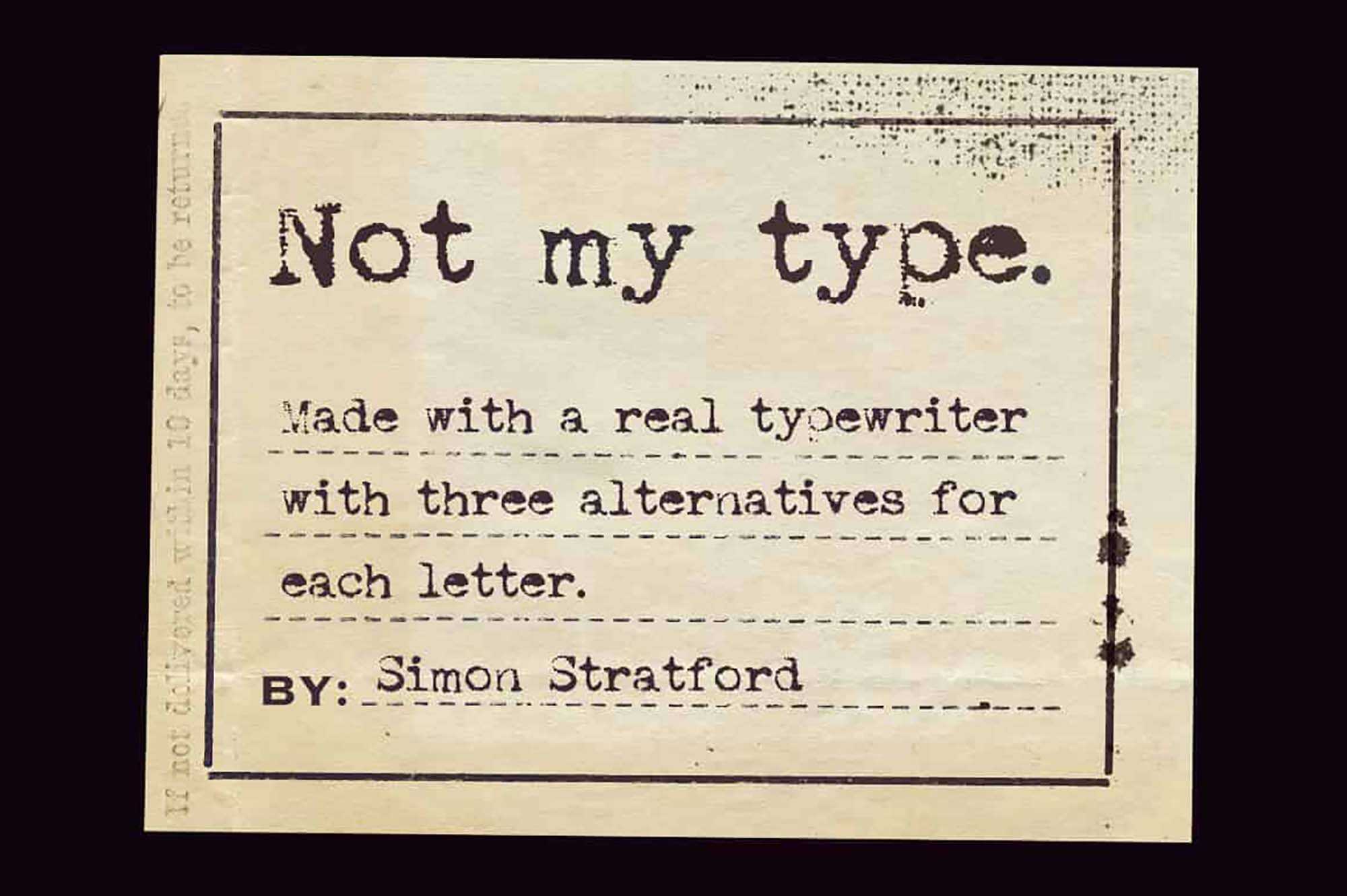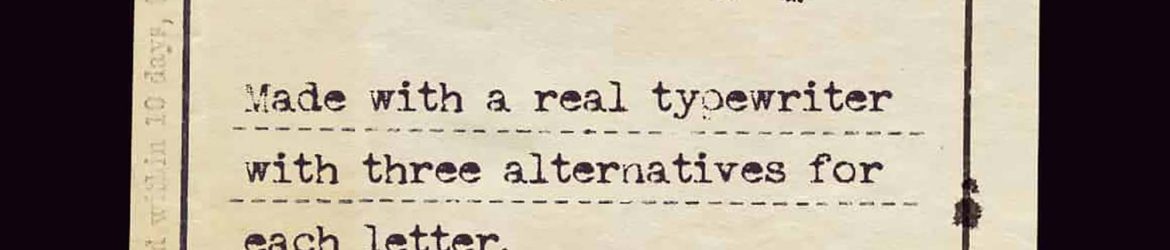
Nós estamos emocionados em apresentar Not My Type Font, uma nova fonte serif criada pelo designer Simon Stratford usando um teclado de escrita real. Essa fonte traz uma experiência única e autêntica, com a versão original e alternativas para cada letra, permitindo-lhe explorar infinitas combinações de texto e tornar seu design mais criativo. Este download inclui uma ampla gama de aplicações para diferentes projetos, desde designs para parede e postais de citações até o uso em blogs e guias de livros, além de logotipos antigos para marcas e editoras. Outra vantagem é o conjunto de letras maiúsculas e minúsculas, oferecendo-lhe uma variedade imensa de opções para personalizar seu projeto. Seja para o seu próximo mural, ou para criar um e-book vintage, Not My Type é o recurso gráfico perfeito para você.